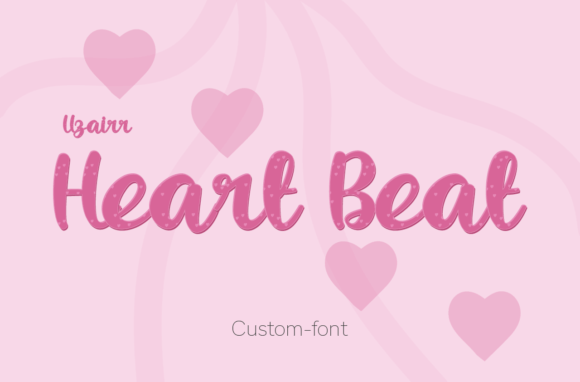
Heartbeat
Heartbeatのような高品質の素材をお探しの場合、このプレミアムパッケージはクリエイティブなプロジェクトに素晴らしい選択です。
精密に作られたHeartbeatは、クリーンなベクター、滑らかなタイポグラフィ、そして安心のための商用ライセンスを提供します。
POD(オンデマンド印刷)製品、結婚式の招待状、またはソーシャルメディアのグラフィックを作成している場合でも、Heartbeatは理想的です。